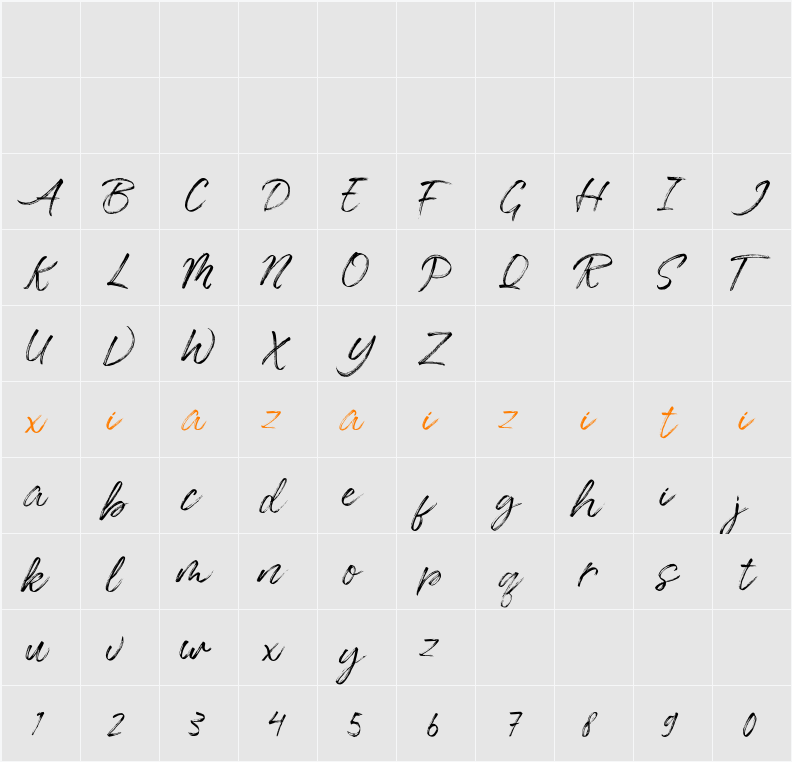
Yohey
Yohey,这款字体结构工整、笔画清晰,兼顾美观与易读性,适用于标题、正文、海报、包装、LOGO 等多种场景。字形优雅稳定,风格百搭耐看,适配日常排版与创意设计,让文字呈现更舒适、更具质感。Yohey一笔一画,皆是细节,以均衡的比例、流畅的线条打造舒适视觉体验,字形端正大气,风格简约现代。无论是商业设计、品牌宣传还是日常排版,都能轻松驾驭,让文字更有格调与力量。Yohey字体下载。
• 制造商: Franstudio
• 设计师: Franstudio